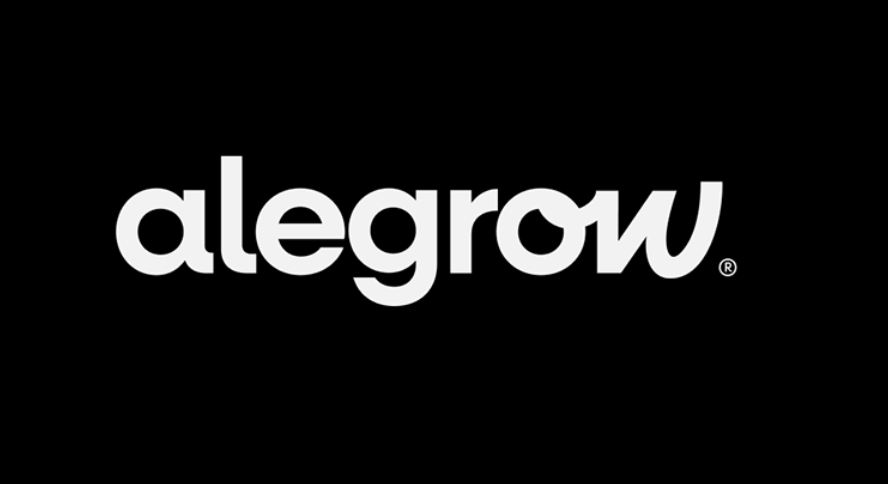
Sans-Serif Font mit Handwriting-Alternates
ich suche eine Sans-Serif Font, welche Handschrift-ähnliche Alternativletter enthält.
Denkbar wäre auch eine Schriftfamilie, welche beide Stile beinhaltet, da ich diese gerne innerhalb einer Wortmarke mischen möchte.
Auch wenn das angehängte Beispiel vielleicht custom-made ist, wäre es schön vielleicht eine Schrift zu finden, mit der ich mein Umsetzen vorhaben kann.
Geht grob in die Richtung, ist dann ja mehr so eine Slab-Serif. Da fehlen mir noch etwas die Details, siehe Übergang vom "o" zum "w" sowie des Schwungs im "w". Vielleicht kann das aber ein guter Ausgangspunkt sein, vielen Dank dir!
Ich habe @ju3lz5000 so verstanden, dass so etwas für die aufrechten Schnitte gesucht wird?
Nein, tatsächlich eine Schriftfamilie, wo Sans-Serif und Handwriting enthalten sind, oder eben alternative Letter (verschnörkelt/Schreibschruft-ähnlich) innerhalb der Sans-Serif.
Ich möchte die Optik des oben gezeigten Logos nachempfinden, um innerhalb des Logos einerseits den wissenschaftlichen (geradliniger Font) und andererseits den emotionalen/menschlichen Bezug (Handwriting) darzustellen, ohne dabei zu kindlich oder verspielt zu wirken.
Das erinnert mich an das Branding von Onlyfy, das EIGA in Hamburg entwickelt haben. Die Schrift ist Custom (basierend auf der Rebond Grotesque) und beinhaltet die von dir gesuchten Handwriting-Alternativglyphen. Vielleicht dient sie dir ja als Inspiration für deine Wortmarke.
Ist das ein Spaßprojekt, Hobby oder sowas oder soll das eine richtige Wortmarke werden?
Was spräche bei einem Logo gegen custom-made :-? Ist vielleicht einfacher als stundenlang nach einer passenden Schrift zu suchen und inspirieren lassen kann man sich von allen (Script-)Fonts, die Ligaturen haben.
Hier findest du z. B. quasi Grotesk-Schreibschriften mit Buchstabenverbindungen:
Und wie die Hope Sans noch eine mit Schwungbuchstaben im Gepäck:
Hier findest Du noch mehr davon:
Es soll eine richtige Wortmarke werden. Da ich typografisch jetzt nicht soo der Crack bin ist es für mich leichter, erstmal nach passenden Fonts zu suchen als mir selbst Buchstaben zusammenzubasteln, die am Ende vielleicht nichtmal gut aussehen 😄